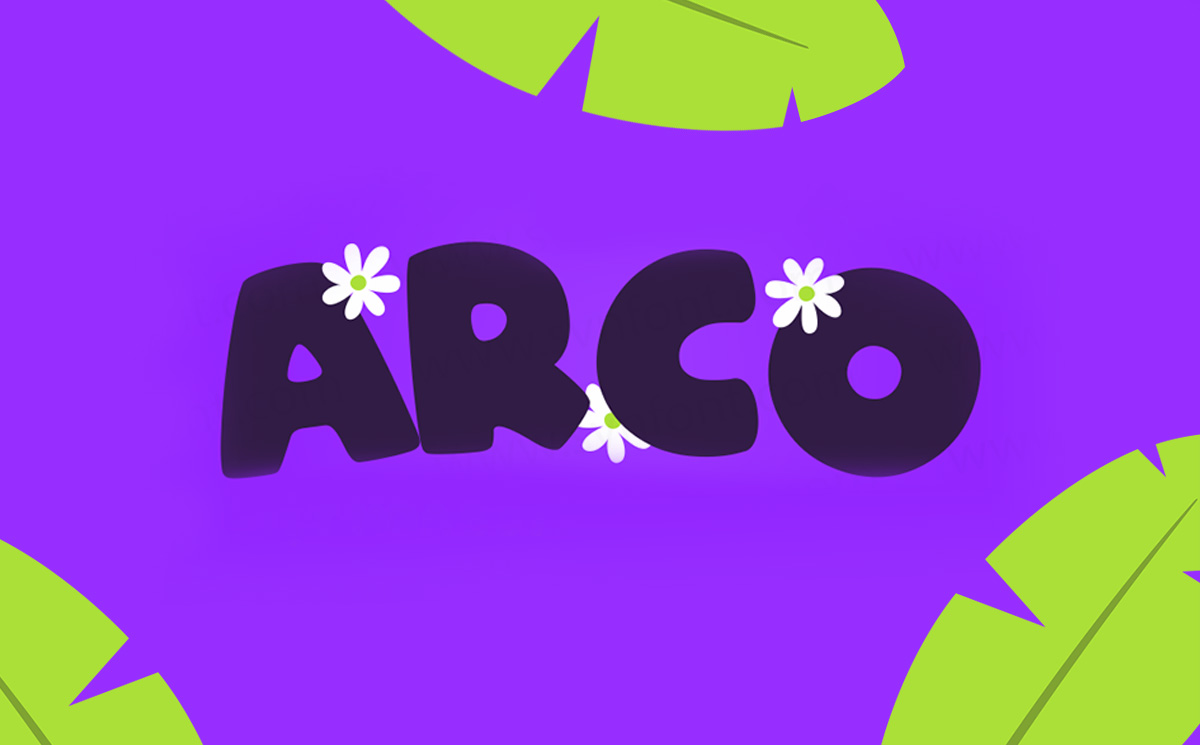
Tải Font Chữ Hoạt Hình Miễn Phí SVN-ARCO Việt Hóa
Tải Font Chữ Hoạt Hình Miễn Phí SVN-ARCO Việt Hóa – Giải Pháp Hoàn Hảo Cho Thiết Kế Vui Nhộn
Nếu bạn đang làm việc với các dự án mang hơi hướng vui nhộn, tinh nghịch hoặc hướng tới đối tượng trẻ em, việc chọn đúng phông chữ là vô cùng quan trọng. Font SVN-ARCO Việt hóa chính là một trong những phông chữ hoạt hình (comic/cartoon) được cộng đồng Designer Việt Nam ưa chuộng nhất.
Font SVN-ARCO Là Gì?
ARCO ban đầu là một typeface mang phong cách Typography đậm chất hoạt hình, với các nét chữ mập mạp và được bo tròn mạnh mẽ. Phiên bản SVN-ARCO là bản đã được nhóm Style Việt Nam (SVN) tiến hành Việt hóa, thêm đầy đủ bộ dấu tiếng Việt chuẩn xác. Nhờ đó, người dùng có thể thoải mái gõ tiếng Việt có dấu mà không lo tình trạng lỗi font hay sai lệch khoảng cách.
Tại Sao Bạn Nên Sử Dụng Font SVN-ARCO?
Phông chữ này sở hữu nhiều ưu điểm vượt trội giúp ấn phẩm của bạn trở nên nổi bật:
1. Phong Cách Hoạt Hình Đặc Trưng
Nét chữ của SVN-ARCO rất dày và chắc chắn nhưng không hề cứng nhắc nhờ các góc được bo tròn mềm mại. Trực quan của font chữ mang lại cảm giác năng động, hài hước và vô cùng thân thiện.
2. Hiển Thị Tốt Ở Kích Thước Lớn
Với độ dày dặn của mình, SVN-ARCO phát huy tối đa sức mạnh khi được dùng làm tiêu đề (Headline) hoặc Text 3D. Chữ hiển thị cực kỳ rõ ràng, bắt mắt ngay cả khi người xem lướt qua nhanh chóng.
Ứng Dụng Của Font SVN-ARCO Trong Thực Tế
Với sự ngộ nghĩnh vốn có, font chữ hoạt hình này là lựa chọn “đinh” cho các hạng mục thiết kế:
• Thumbnail YouTube: Tạo tiêu đề to, rõ, giật tít cho các video giải trí, vlog hoặc gaming.
• Sách báo, Truyện tranh: Làm font chữ bìa sách thiếu nhi, truyện tranh comic hoặc các ấn phẩm giáo dục mầm non.
• Thiết kế Game: Sử dụng làm UI text hoặc logo cho các tựa game mobile mang phong cách casual, vui nhộn.
• Bao bì sản phẩm: Phù hợp với vỏ hộp bánh kẹo, đồ chơi trẻ em hoặc thời trang kids.
🌟 Đặc điểm “ăn tiền” của SVN-ARCO:
• Nét chữ to bản, bo tròn cực kỳ thân thiện và mang đậm chất Cartoon/Comic.
• Làm Headline, tiêu đề to, chữ 3D thì cứ gọi là “nhức nách”, siêu nổi bật!
• Đã được SVN Việt hóa chuẩn 100%, gõ tiếng Việt mượt mà trên mọi phần mềm (Photoshop, AI, Premiere, CapCut, Canva…).